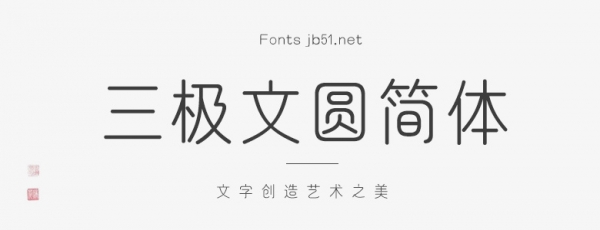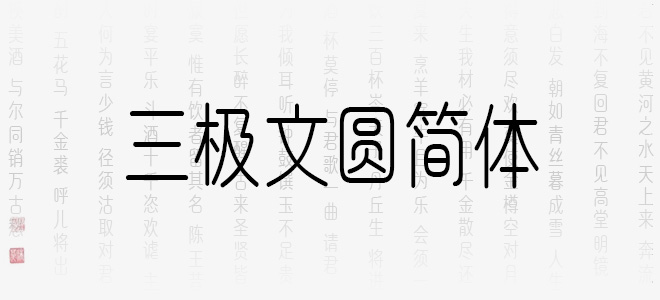
三極文圓簡體作品整體風(fēng)格獨(dú)特,具有古法圓通、樸拙之感,字形融合了象形、篆書等古樸字形,使其風(fēng)格簡潔明快,獨(dú)具一格。字體輕巧簡潔,古拙而不凡。粗細(xì)勻稱,起筆收筆為圓頭,折、鉤、撇捺轉(zhuǎn)折圓潤飽滿,具有古拙婉轉(zhuǎn)的氣質(zhì)。視覺效果簡潔易識別,實(shí)用性強(qiáng)。本作品適用于傳統(tǒng)印刷媒介的標(biāo)題與正文排版,尤其適用于古典、工藝類型行業(yè)和書籍裝幀。
三極文圓簡體